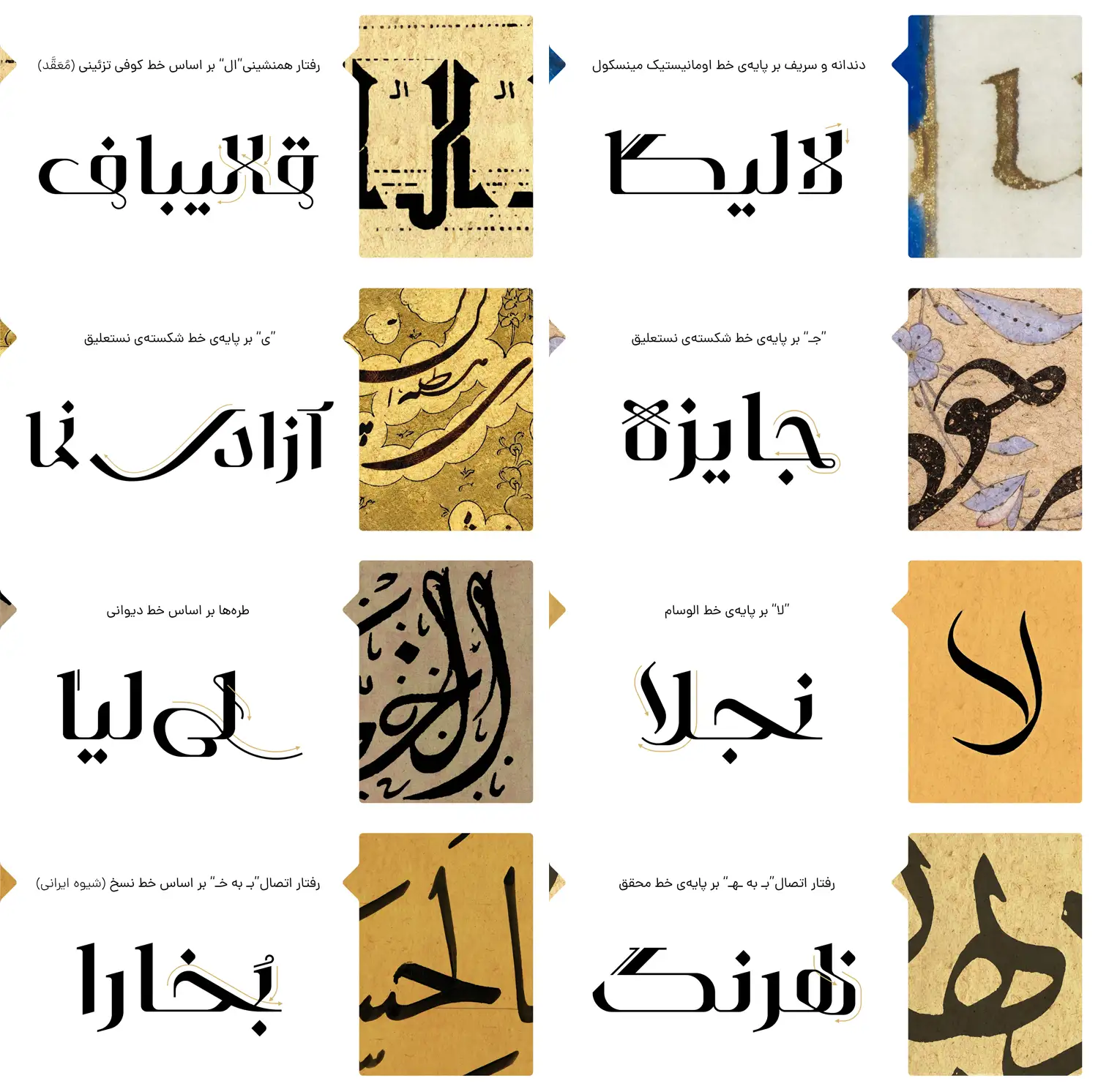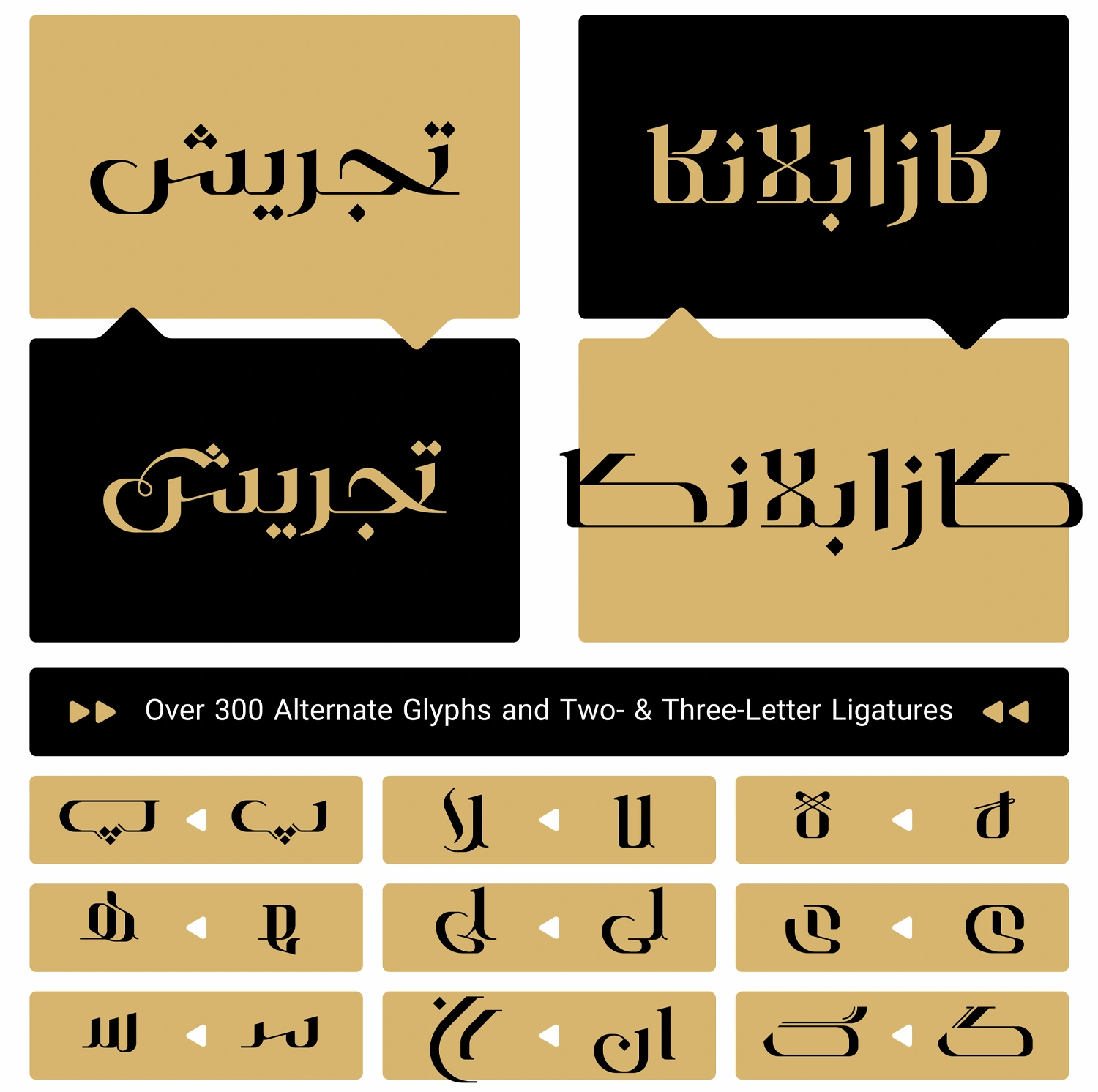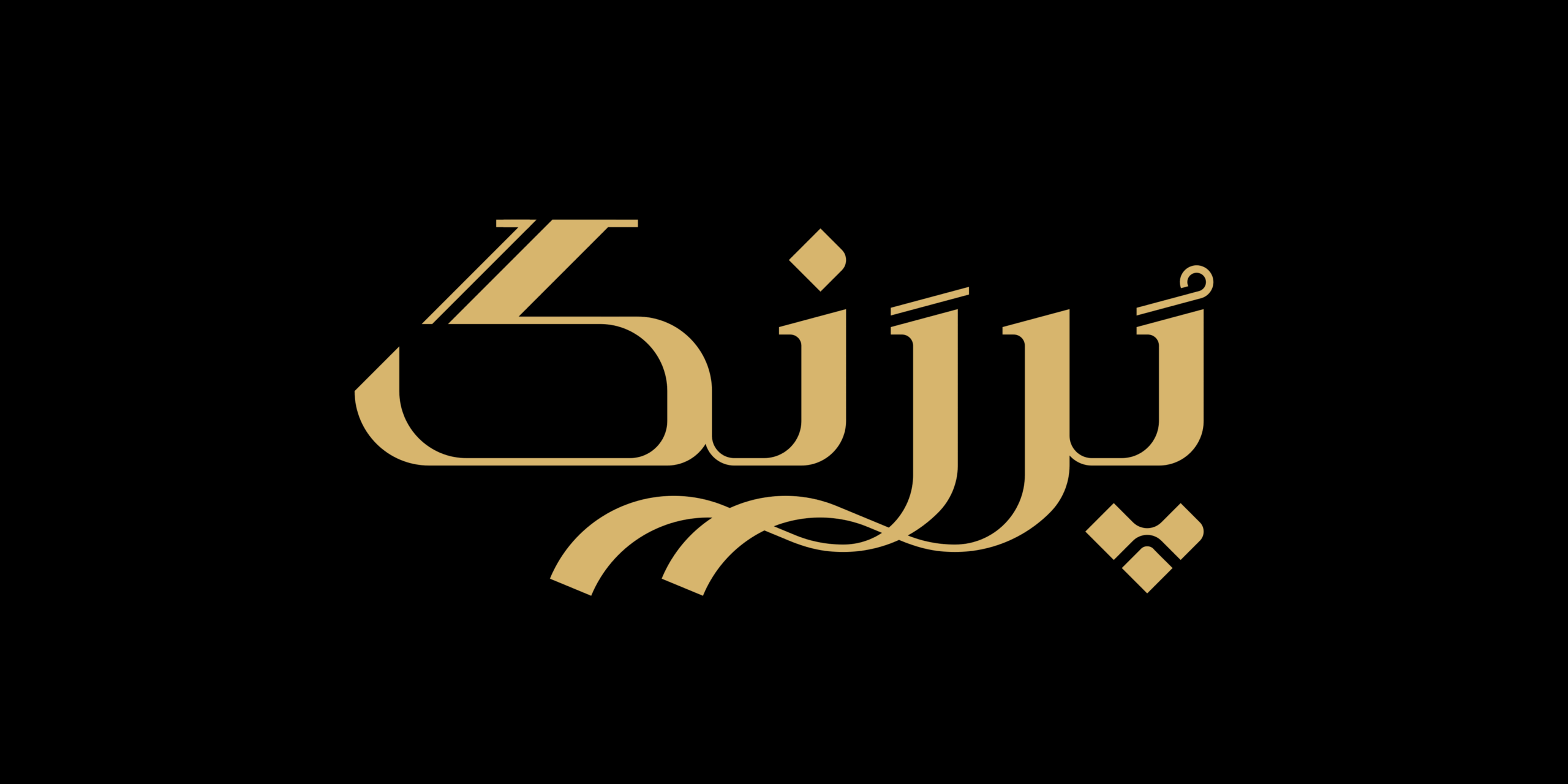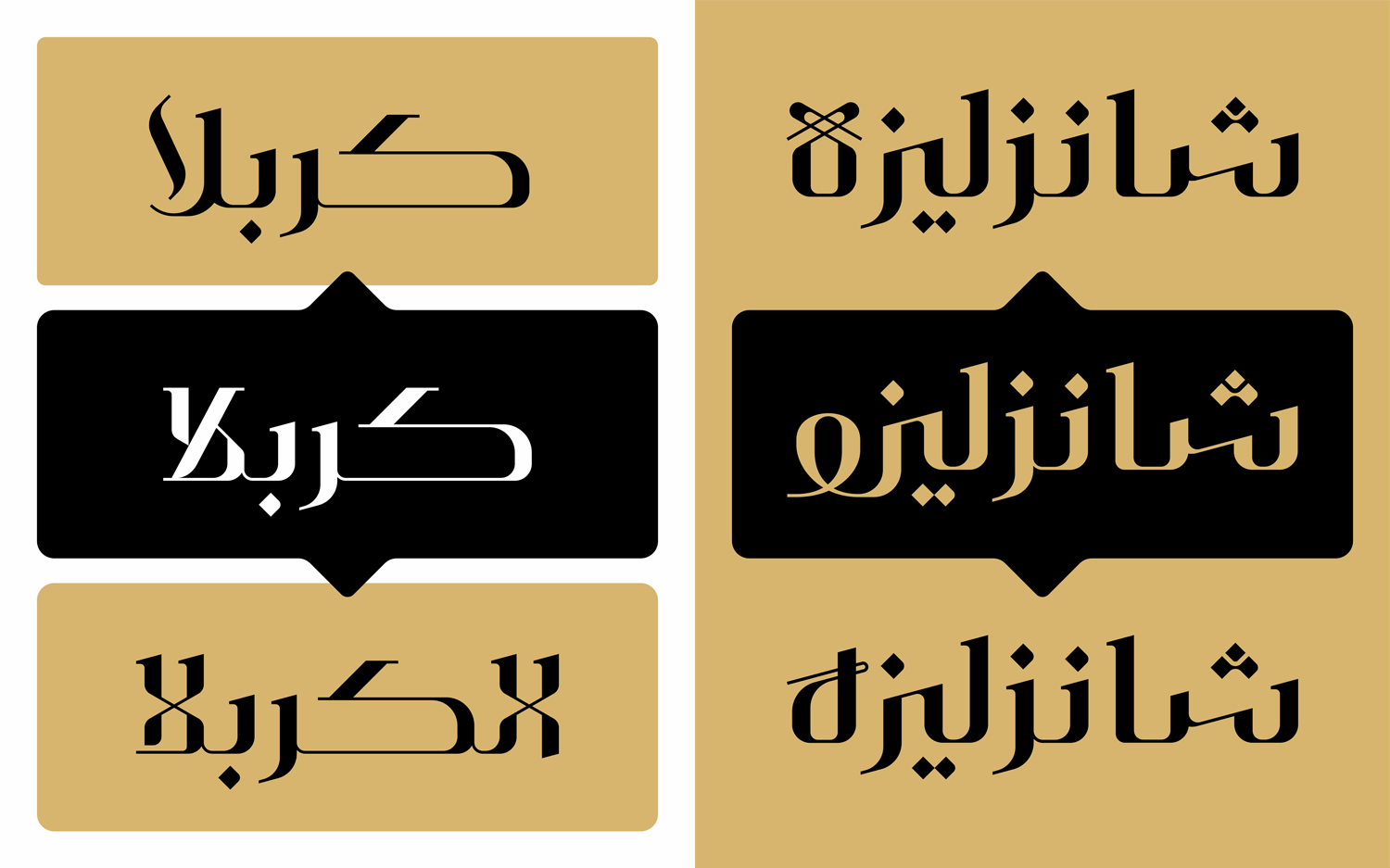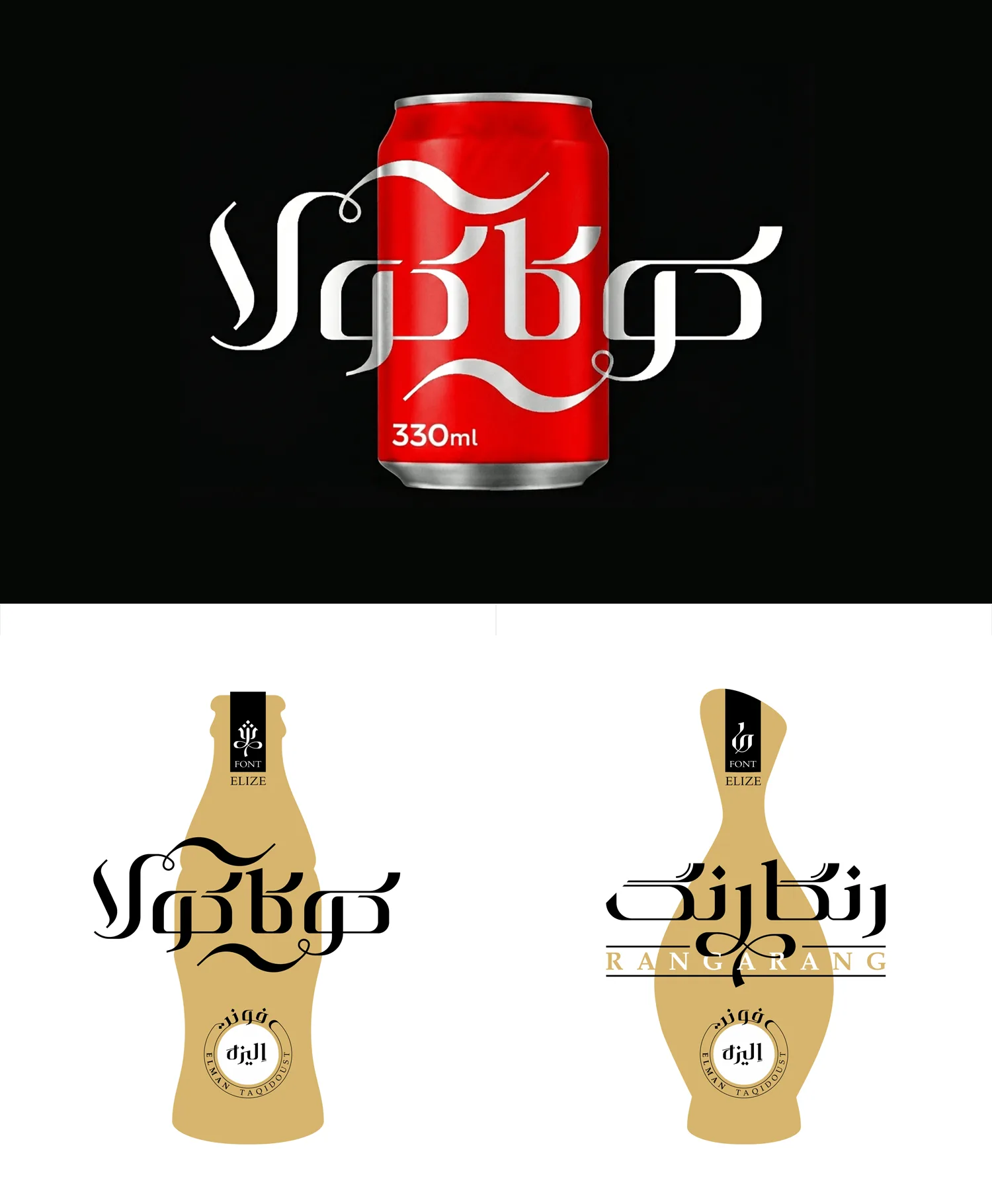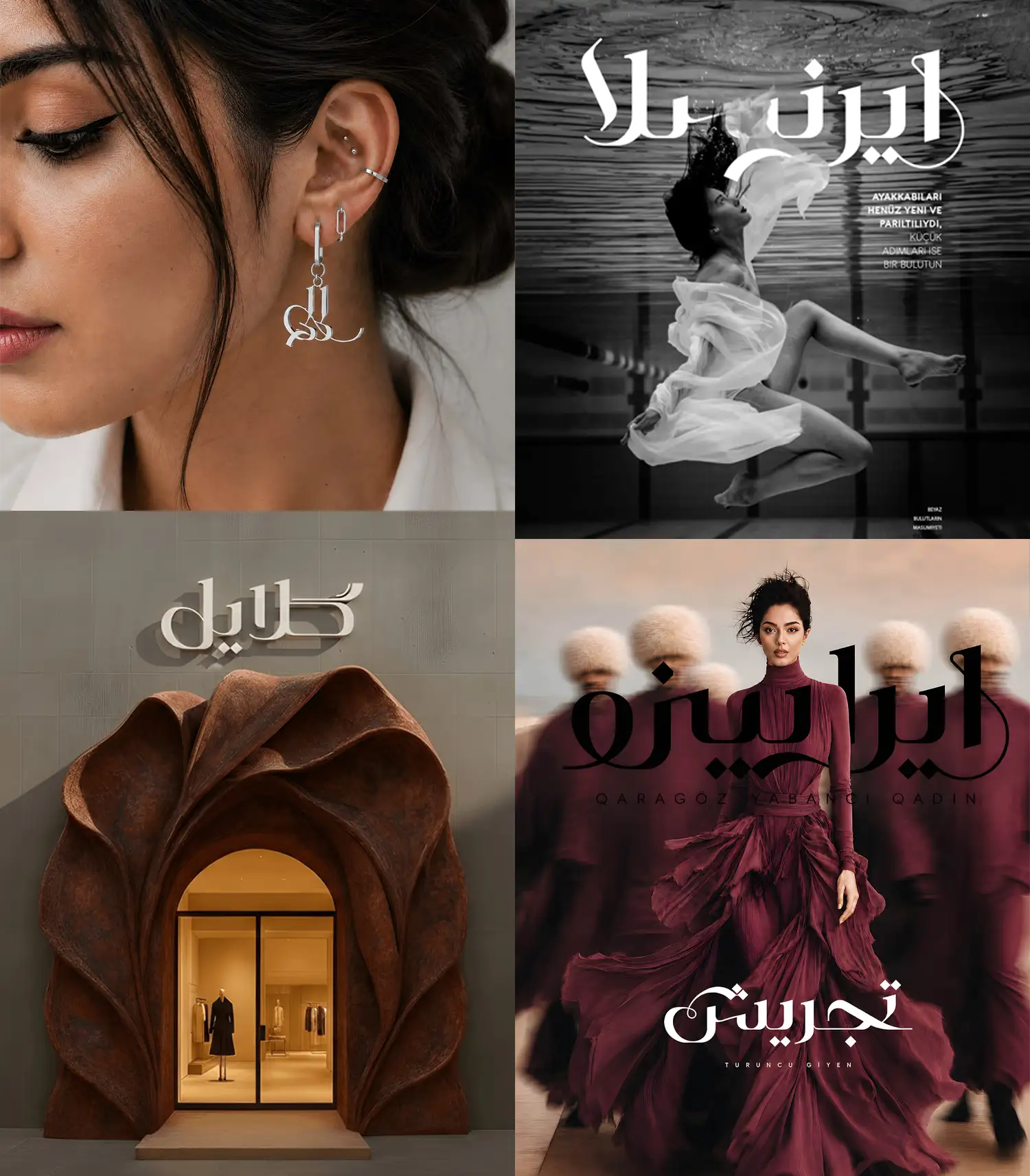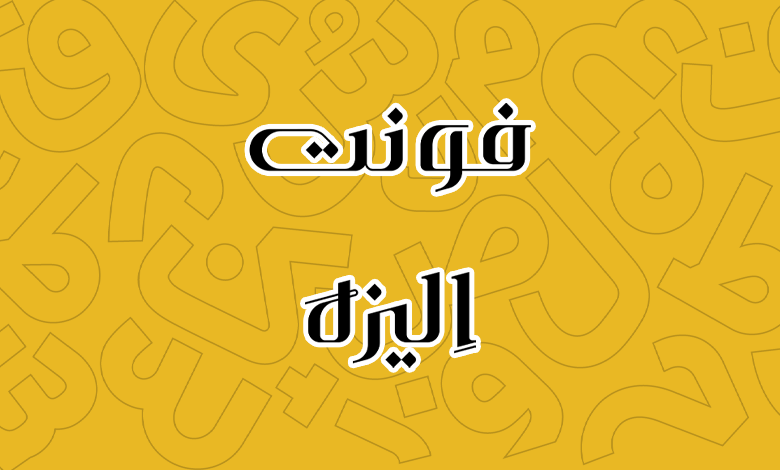
فونت الیزه (Elize)
| طراح | ائلمان تقی دوست، امین عابدی |
فونت الیزه (به انگلیسی: Elize) قلمی هندسی و الهام گرفته از فونتهای کلاسیک انگلیسی است که حروف لوکس با با هندسهی دقیق غربی با خوشنویسی ایرانی و عربی ترکیب کرده تا شاهد یک فونت لوکس باشیم. نظم و ساختار حروف در این فونت به شکلی است که ساختاری بسیار نمایشی از خود برجای میگذارد.
در فونت الیزه حروف به شکلی خاص و منظم با اتصالاتی زیبا به یکدیگر گره خوردهاند. اتصالاتی که جدای از ساختار استاندارد حروف فارسی و عربی، با ادغام ترکیبات جایگزین شکل کلی کلمات را دگرگون و زیباتر میکند تا در آثاری که در زمینه عناوین، تبلیغات و پوسترهای تبلیغاتی مورد استفاده قرار میگیرد، یک ظاهر کاملا نمایشی فراهم کنند.
چنین ویژگیهایی فونت Elize را به قلمی کاملا ایدهآل برای خلق لوگوتایپهای جسورانه و هویت بصری تبدیل کرده است. بهویژه در حوزه صنعت و مد برندهای لوکس که استفاده از چنین ساختاری بر پایه هویت بصری برندهای خارجی بسیار مورد توجه قرار گرفته است.
نقد و بررسی فونت الیزه (Elize)
الیزه را نمیتوان صرفا یک فونت الهام گرفته از خطوط انگلیسی درنظر گرفت. این فونت با ادغام از چندین سبک نوشتاری و ترکیب با سبک نوشتاری ایرانی و عربی خلق شده است. از جمله دندانهها و سریفهایی که بر پایه خط اومانیستیک مینسکول هستند. یا در ترکیباتی مانند «ال، کـ» که از خط کوفی تزئینی الهام گرفته شده است.
به منظور ایجاد اصالت ایرانی در این فونت حرف «ه» پایانی بر پایه خط رقاع و «جـ، ی» بر پایه خط شکسته نستعلیق طراحی شده است. چنین ترکیباتی بهوفور در طراحی این فونت مورد استفاده قرار گرفته شده که برخی از آنها را در تصاویر بالا مشاهده میکنید.
فونت الیزه از زبانهای فارسی، عربی، کوردی و ترکی پشتیبانی میکند. دارای یک وزن Regular است؛ اما از نظر وزن ظاهری ساختاری سیاه از خود نشان میدهد. اعداد فارسی و عربی به شکل استاندارد در این فونت پیادهسازی شده است و میتوانید از فرمتهای مختلف TTF, WOFF و WOFF2 به صورت استاندارد در محیطهای مختلف نرمافزاری گرفته تا وب از این فونت خلاقانه و جسور استفاده کنید.
طراحی این فونت توسط ائلمان تقی دوست انجام گرفته و امین عابدی که سابقه همکاری با دیگر طراحان فونت فارسی را دارد، توسعه نرمافزاری این قلم را انجام داده است. از آنجا که نقد و بررسی این فونت نیازمند حوزه تخصصی و آشنا به تاریخچه حروف در فرهنگها و ملل مختلف است، در ادامه بر اساس تصاویر و محیطهایی که این فونت برای آن خلق شده است، شما را با آن آشنا میکنیم.